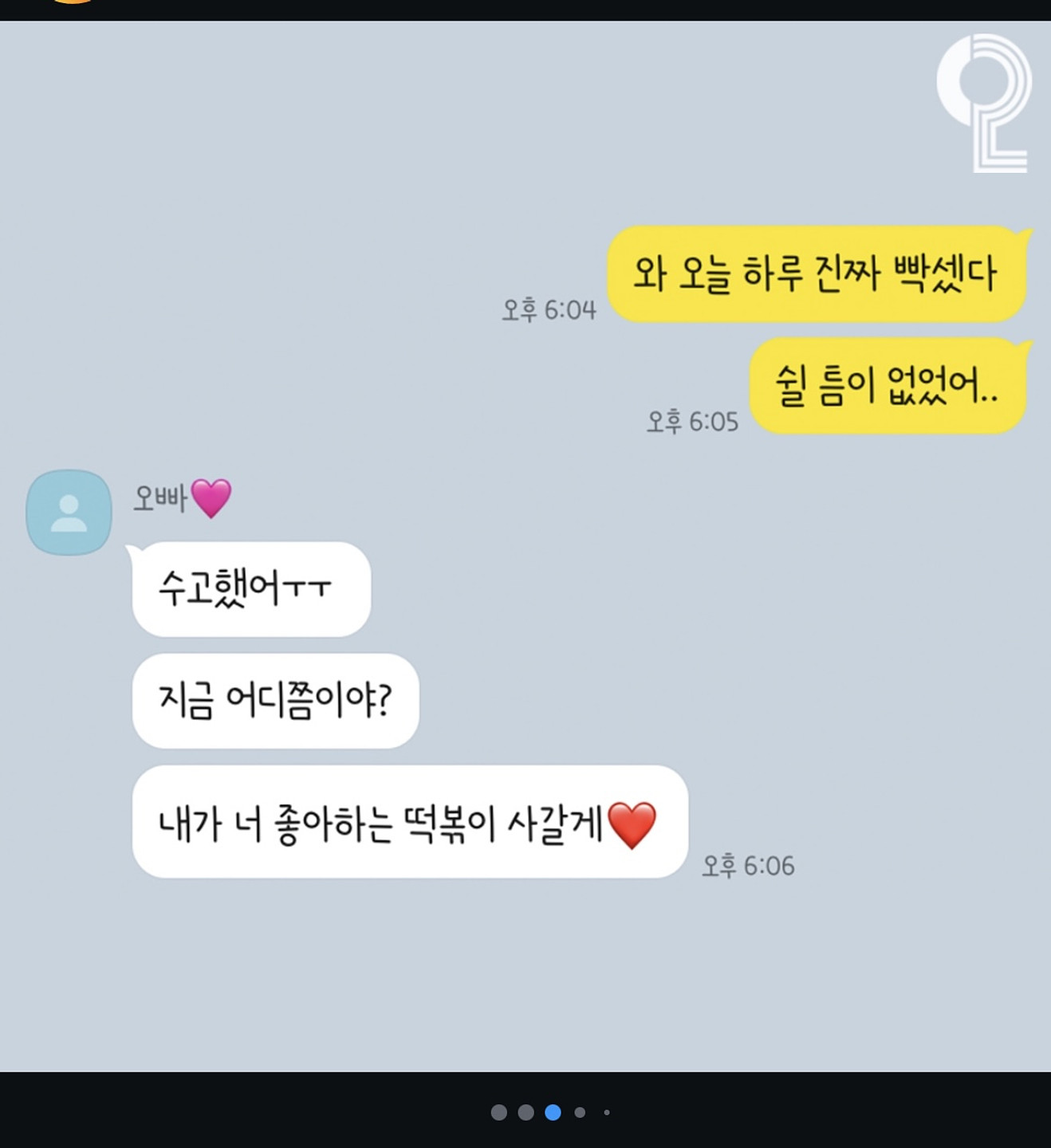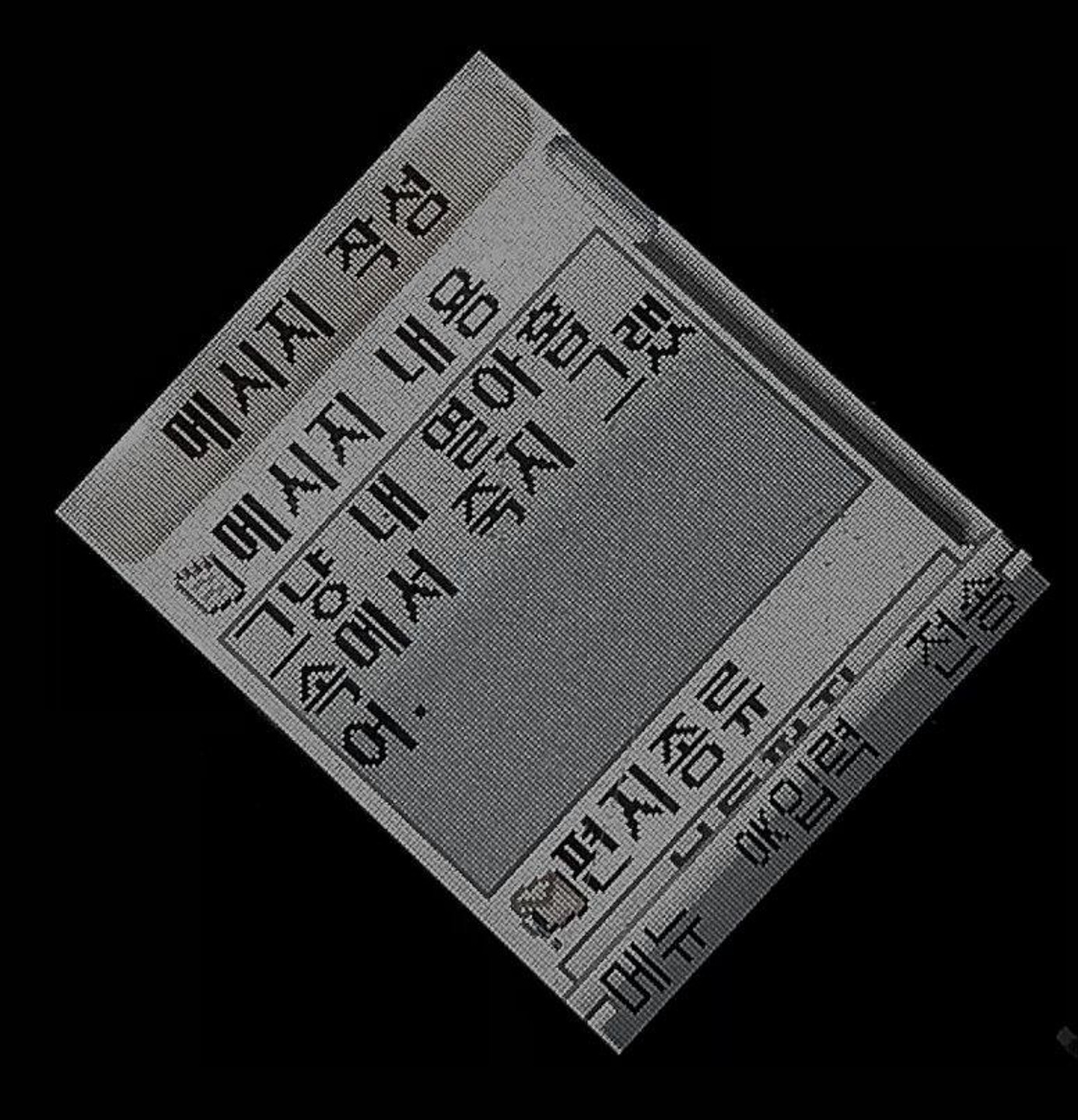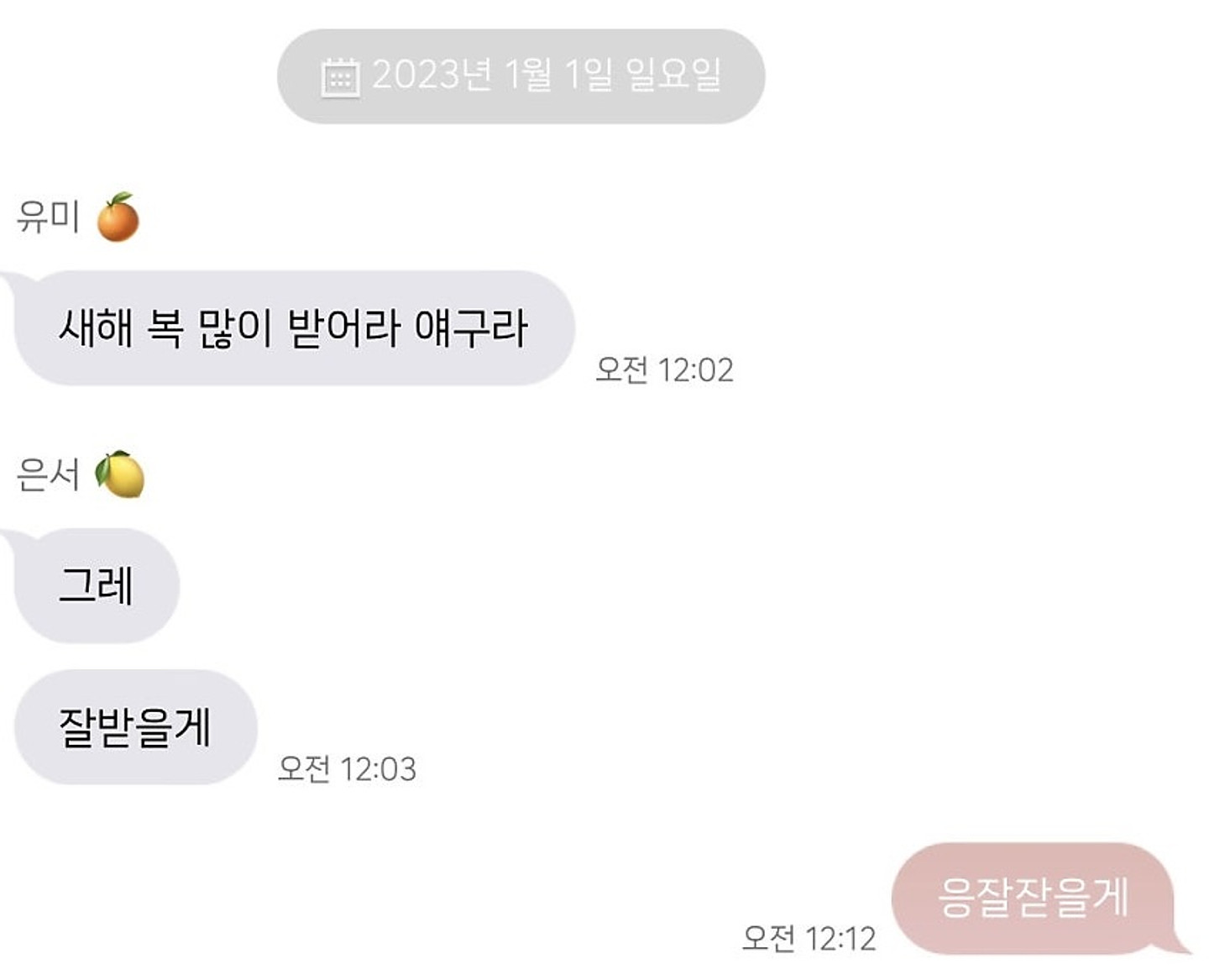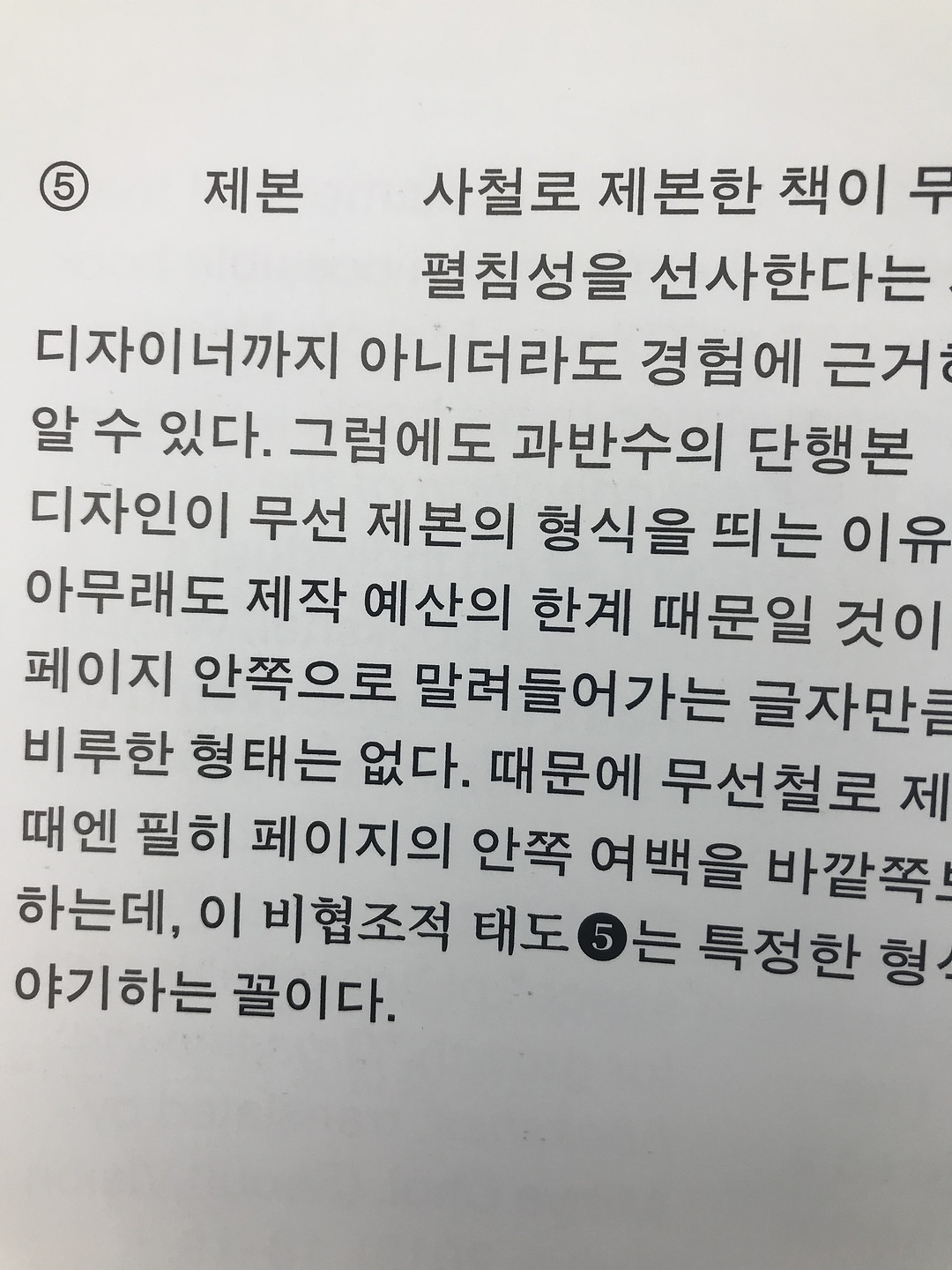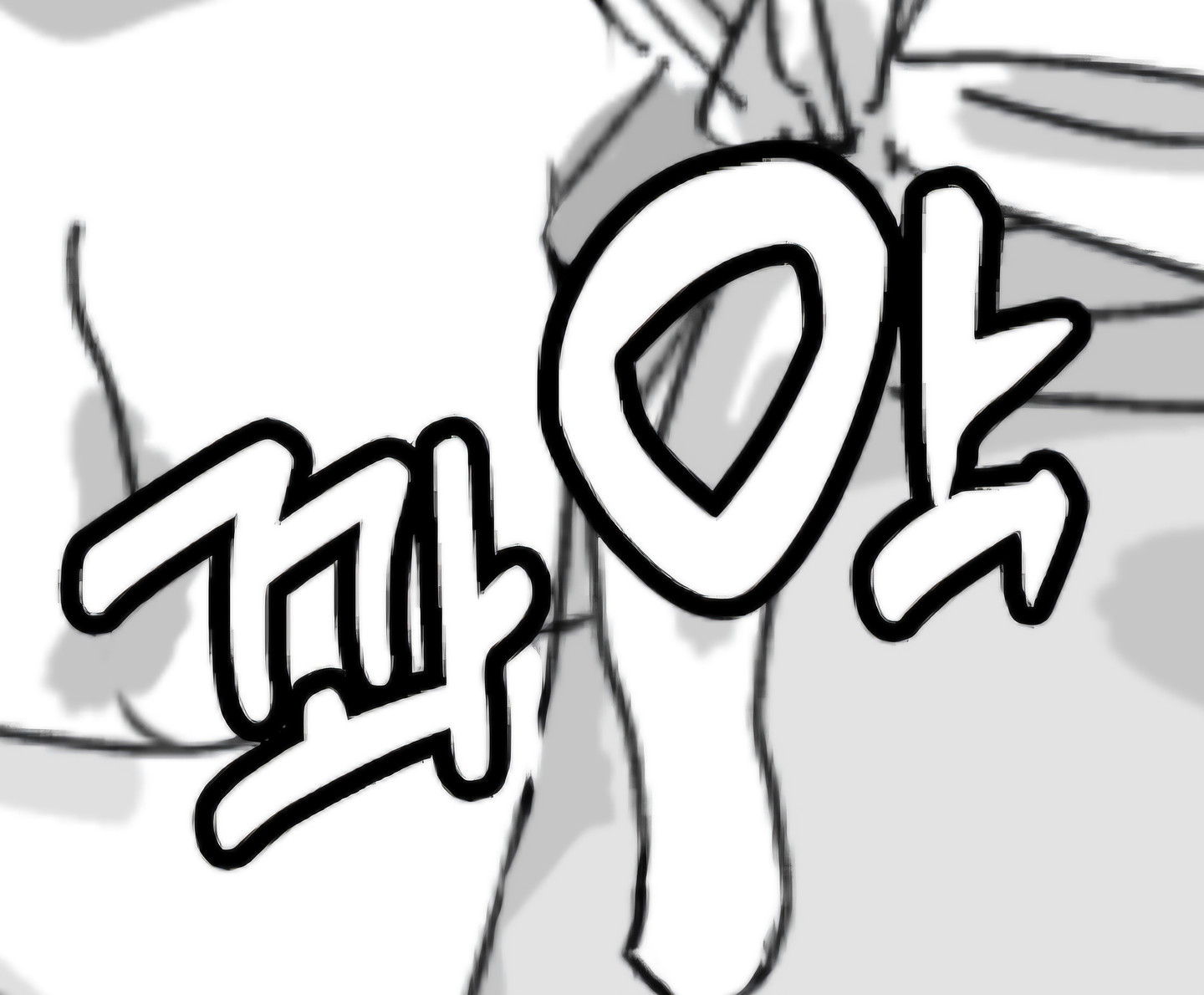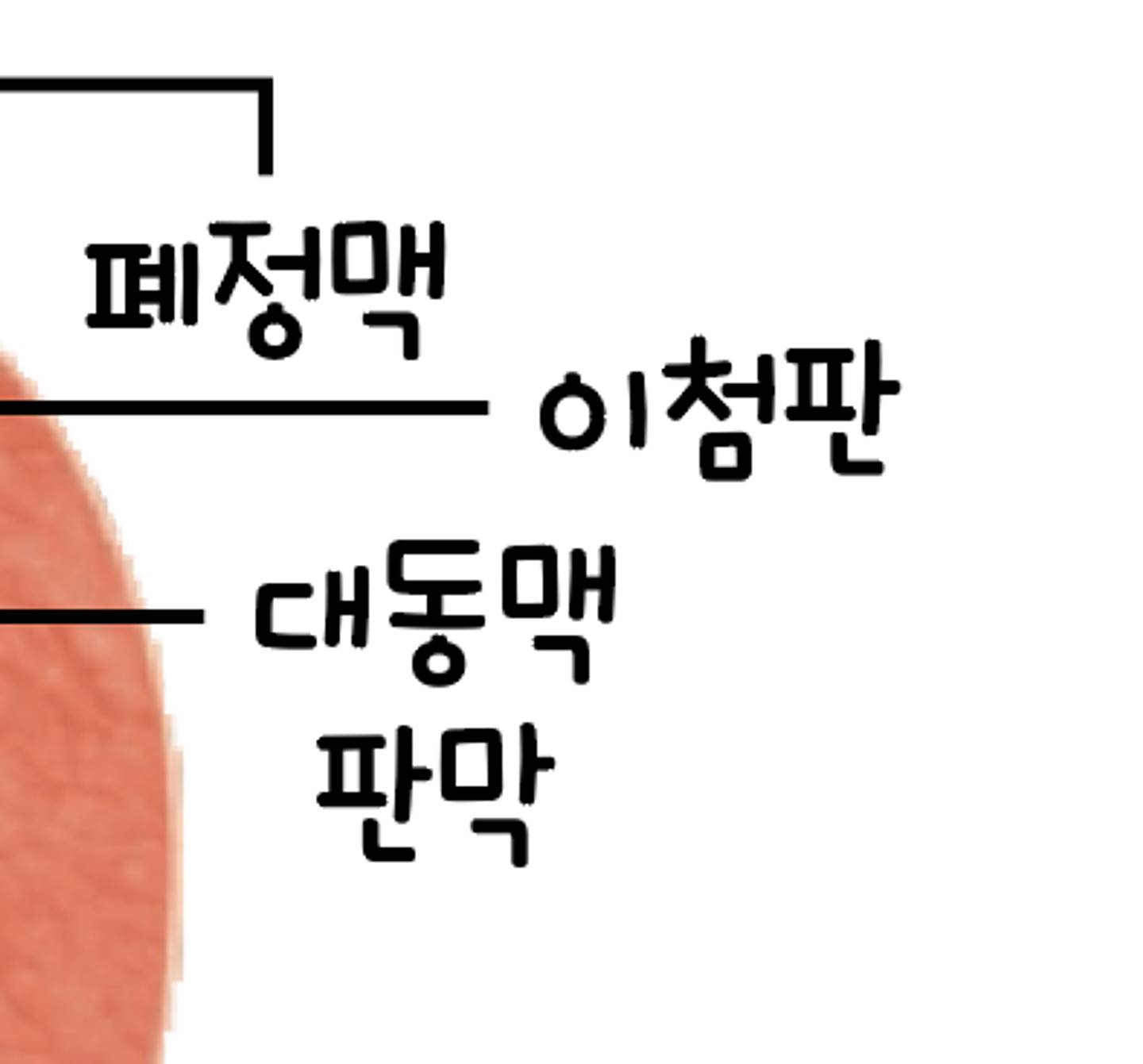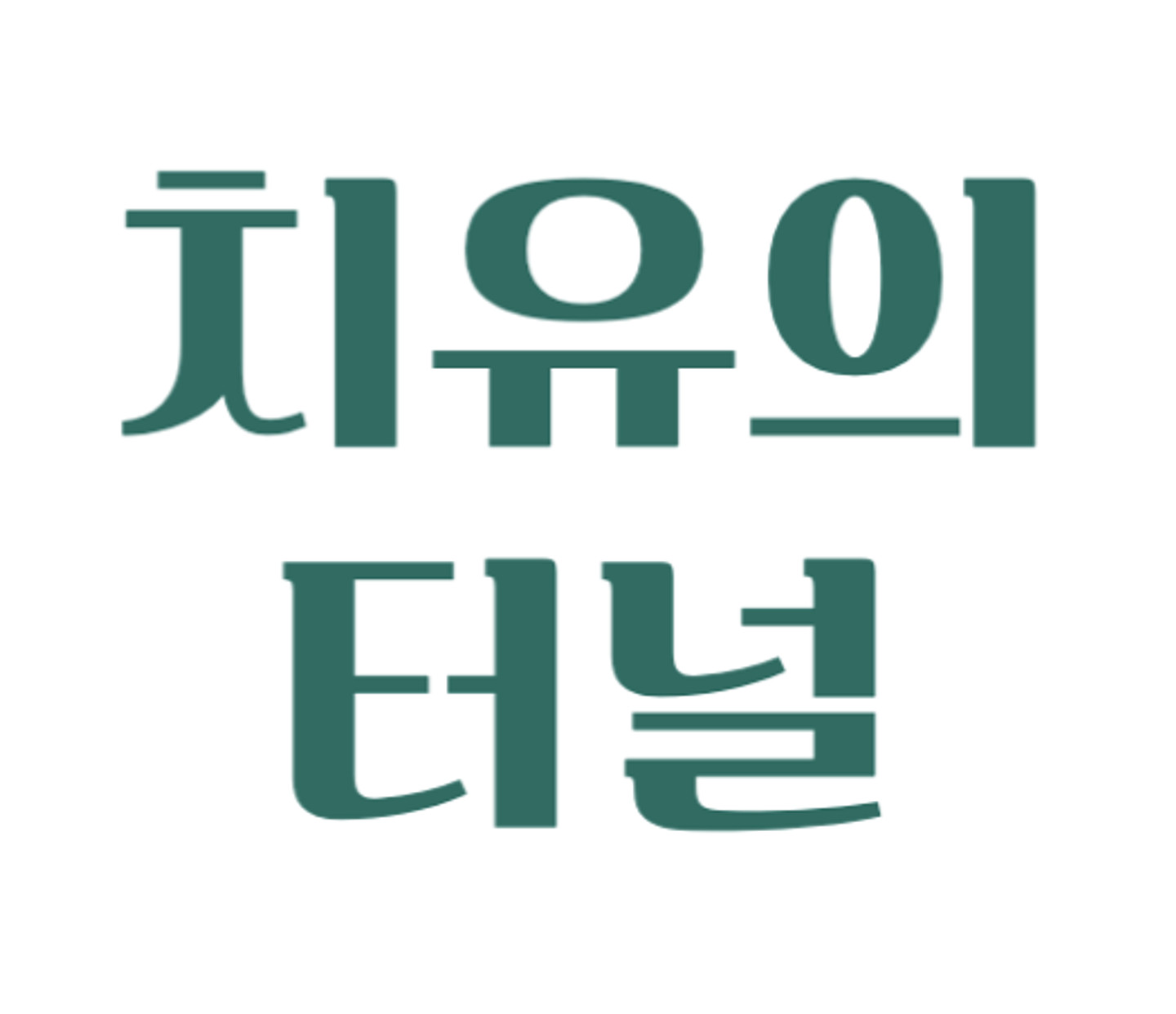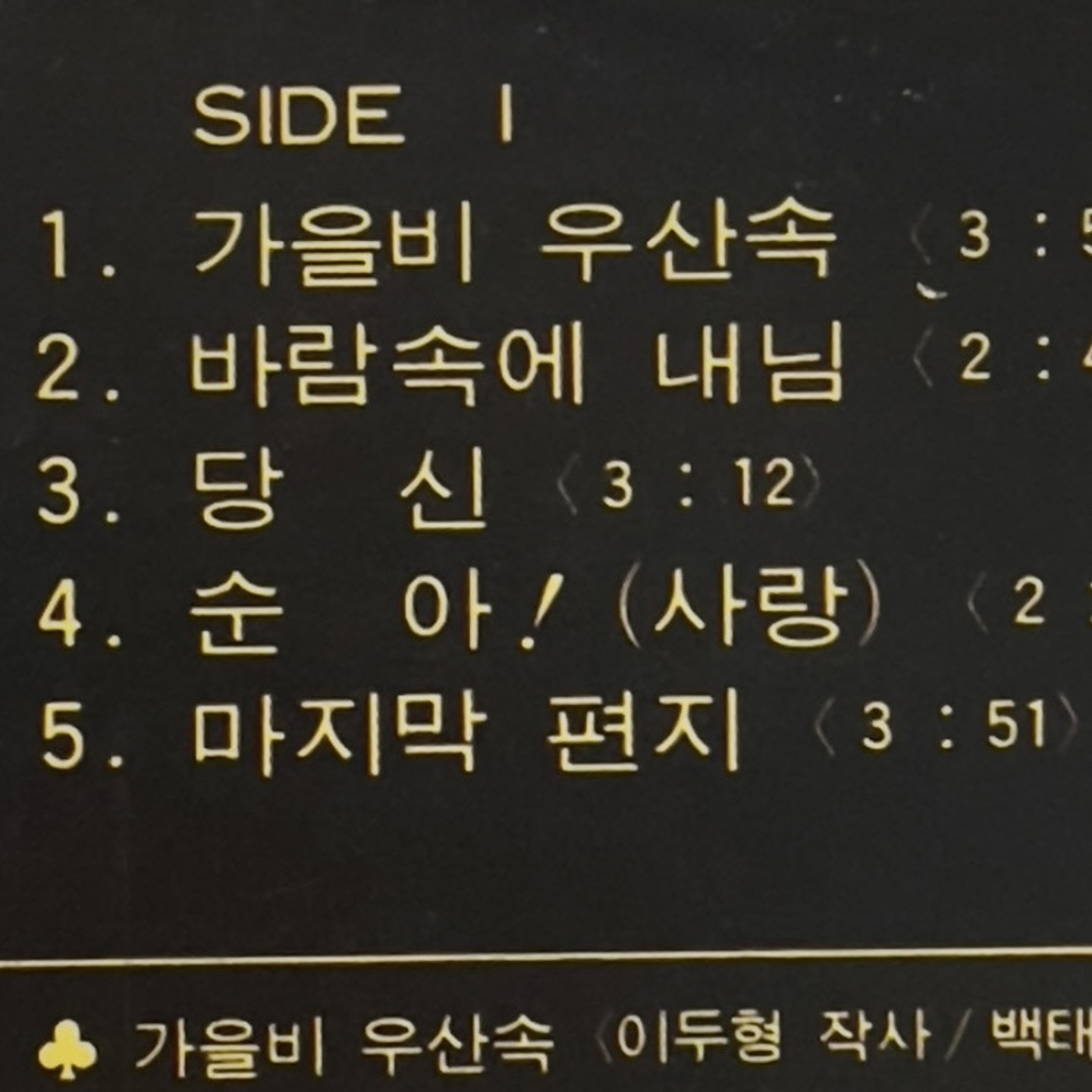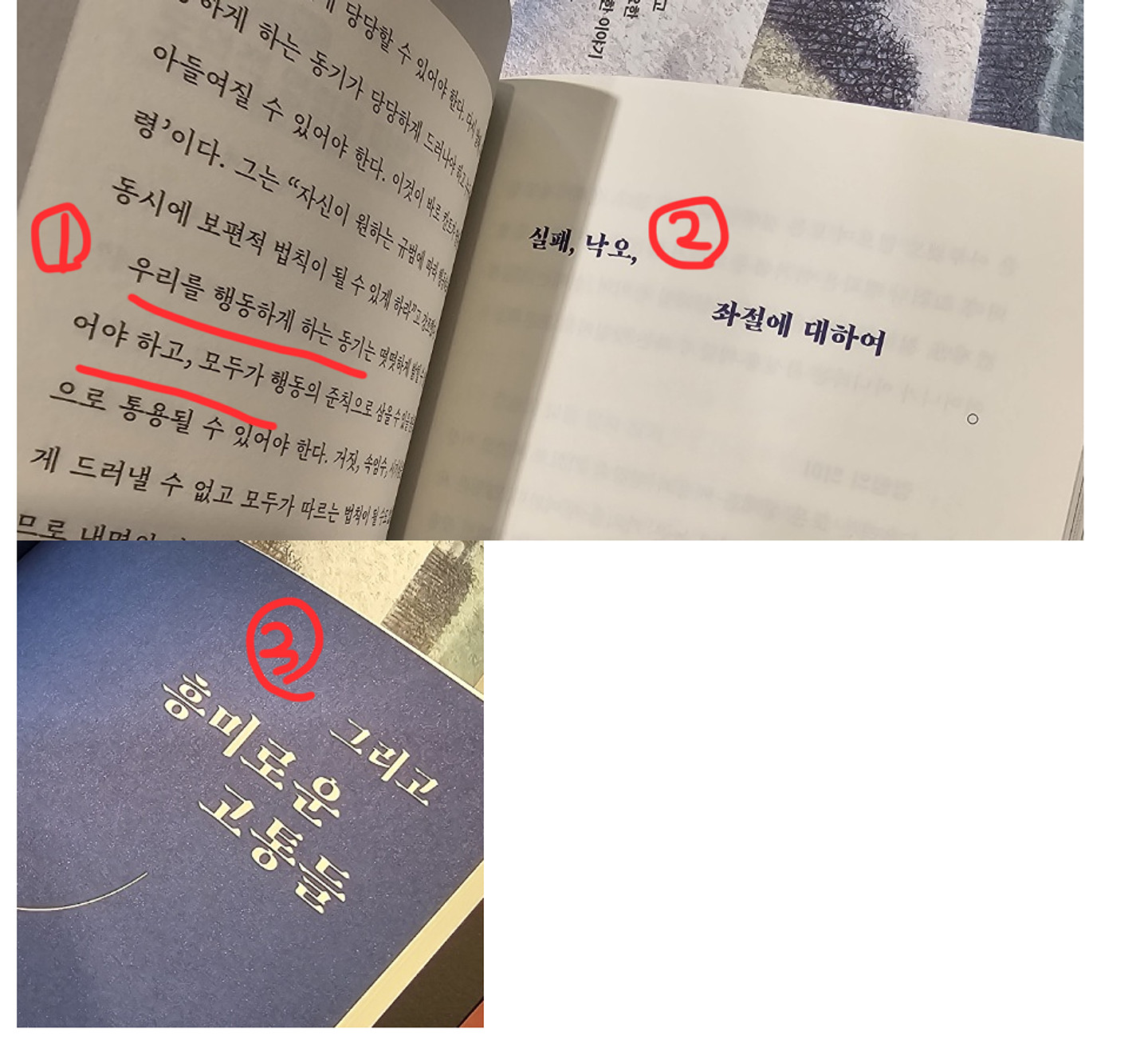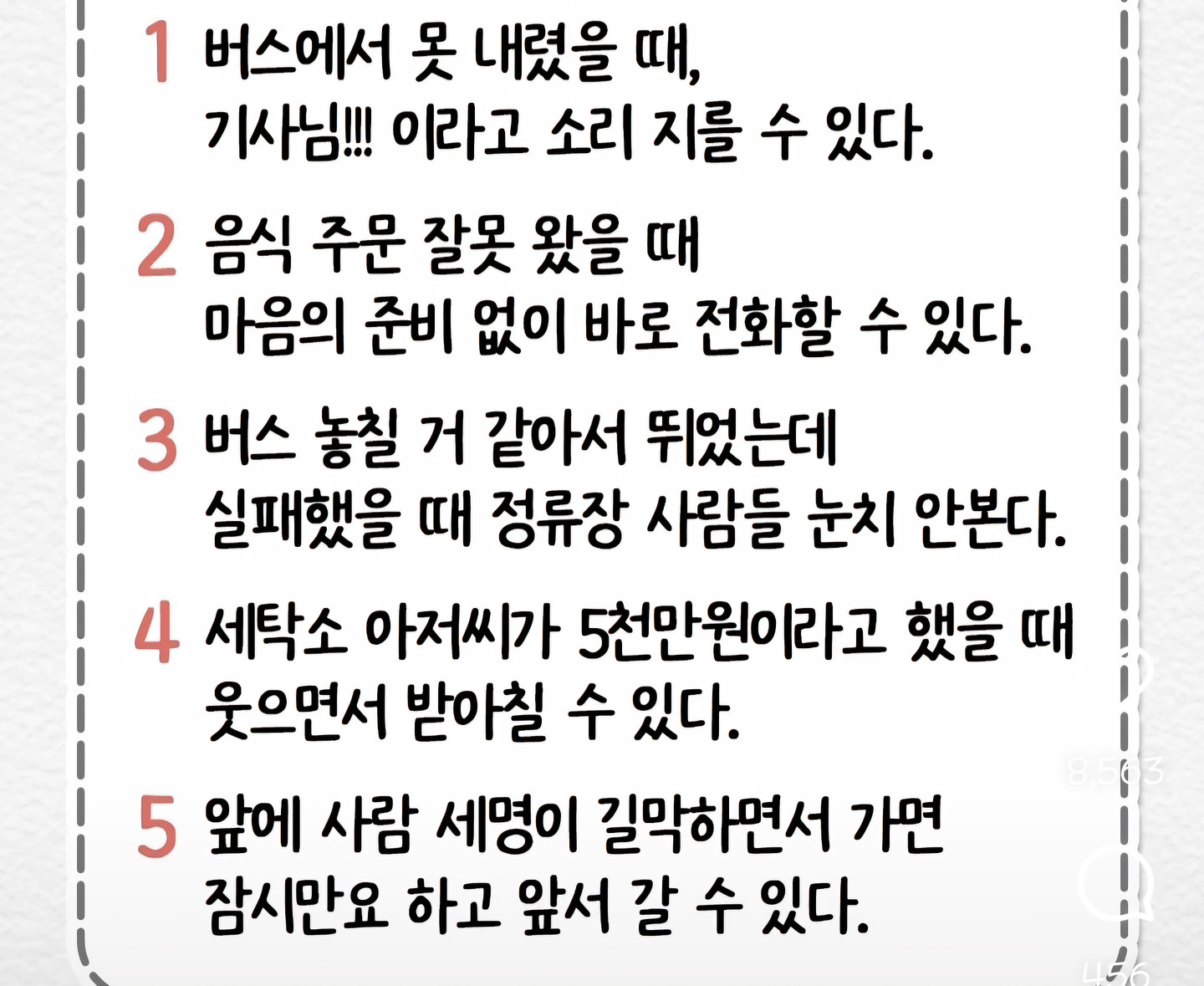
어떤 글씨체인지 궁금해요(일본어도 아마 포함된 거 같아요).
이 폰트 이름이 뭔가요ㅠㅠ 스타벅스 랜더스 이벤트 페이지에 있던 폰트에요!
이 폰트 알고계신분 계실까요~? 너무예뻐서 구매하고싶은데 어떤폰트인지 도통모르겠어요ㅠㅠ도움부탁드립니다~! 미리 감사드립니다:)
이거 폰트 혹시 뭔지 아시는분 계신가요🥺🥺
궁금합니다>_<!
일상의실천 포스터 폰트 무엇인지 아시나요?
한글과, 영어 폰트가 궁금합니다
이거 무슨폰트일까요?ㅠㅜ
굵은 영문 폰트 뭔지 알 수 있을까요?
이 폰트 무슨 폰트일까요??ㅜㅜㅜㅜㅜ
이 글씨체 이름 알려주시면 감사하겠습니다
채널십오야에서 쓰인 폰트인데 자막 글씨체 너무 궁금합니다
급해요 무슨 폰트일까요?
폰트 이름 뭔가요.. 너무 예쁘네요
폰트명 궁금합니다. 알려주시면 감사하겠습니다.
굵은 폰트 얇은 폰트 둘다 궁금해요!!
궁금해요 아시는 분들 계시면 도와주세용 ㅠㅠ
안녕하세요 이 폰트 아시는 분 계실까요? 궁금합니당!
어떤 글씨체일까요? 상업적으로 이용이 가능할까요?
무슨 폰트에요
이 폰트 다른데서도 몇 번 봤던걸로 기억해서요! 폰트 이름이 어떻게 될까요?
참고로 정신이 들어요? 이제부터 혼자 사셔야 해요 라는 책에 쓰인 폰트입니다! 궁금해요
북유럽신화 책 폰트 오딘과 미미르 폰트가 궁금해요
KTX 기차 티켓에 적힌 폰트입니다. 알려주시면 감사하겠습니다 ... (코레일, KTX, 기차, 기차표)
헤어질 결심 크레딧 폰트인데 이름 알 수 있을까요?!
이 폰트 무슨 폰트일까요?! 위에 이름 폰트랑 오르막길 폰트가 다른 폰트라면 두 폰트 다 알려주실 수 있을까요?
온글잎 폰트 같은데 이거 무슨폰트인가요ㅠ
썸네일 폰트 뭔지 궁금해요ㅠㅠ
이거 분홍글씨 폰트 뭔가요...?
요 필기체 같은 폰트 몬가용??ㅜㅜ
화정역 폰트
이거 무슨 폰트 인가요?약간 그 시절 그 느낌인데 픽셀 관련?폰트 같아요
비싸다는 편견을 깨버린 ㅡ 이거 무슨 폰트일까요
해당 폰트가 뭔지 알고 싶습니다 🥲
해당 폰트 찾고 있습니다ㅠㅠ 눈누엔 없는 폰트 같은데... 혹시 그냥 손글씨일까요??ㅠ
네이버 라운드 고딕인지 헷갈립니다
무슨 폰트인지 아시는 분 계신가요ㅜㅜ 아니면 저렇게 꽉 채울 수 있는 비슷한 폰트라도...
이 폰트가 뭔가요?
이 폰트 무엇인가요?
저 사진 외에 다른 사진은 없습니다. 알려주시면 정말 감사하겠습니다
무슨 폰트에요ㅠㅠ
너무 예쁜데 무슨 폰트에요??ㅠㅠ
이거 무슨 폰트에요ㅠㅠㅠ
폰트 궁금해요..
이 폰트 궁금해요 혹시 컴퓨터만 지원하면 비슷한 모바일 무료폰트 추천해주세요
제목에 쓰인 폰트가 너무너무 알고싶어요.. 저런 날카로운 느낌의 한자 명조체를 찾기 너무 힘들어요 ㅠㅠ
신동엽 짠한형에 나오는 자막 폰트인데, 어떤 폰트인지 궁금합니다.
무슨 폰트일까요? 손글씨려나..
궁금합니다! 고수님들 부탁드려요^^
이 폰트 궁금해요!!
compadres <- 이 폰트 너무너무 찾고 싶어용ㅜㅜ
이거 무슨 폰트일까요?ㅠㅠ
알려주세용 🥰
이건 뮤슨 폰트일까요?